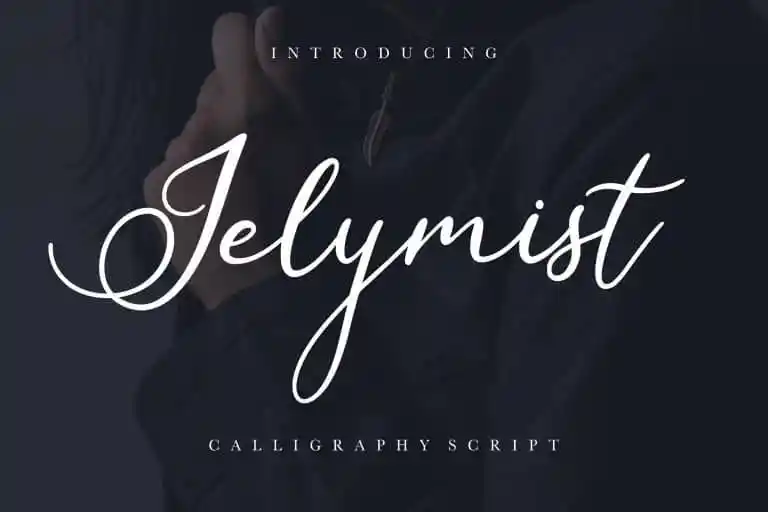
Jelymist Calligraphy Font
Jelymist Calligraphy Font é uma fonte elegante criada por Creatype Studio que traz a sofisticação dos traços tipográficos com um toque mágico de pressão. Ideal para projetos de marca, logomarcas, designs de casamentos, posts nas redes sociais, anúncios, embalagens de produtos e design em geral. Suave e moderna, ela é perfeita para qualquer tipo de projeto que deseje uma sensação autêntica e pessoal da escrita à mão. Jelymist não apenas revolucionará sua fonte de marca, mas também fornecerá um toque único para suas criações digitais, garantindo que cada projeto seja apresentado com a elegância e personalidade que merece.